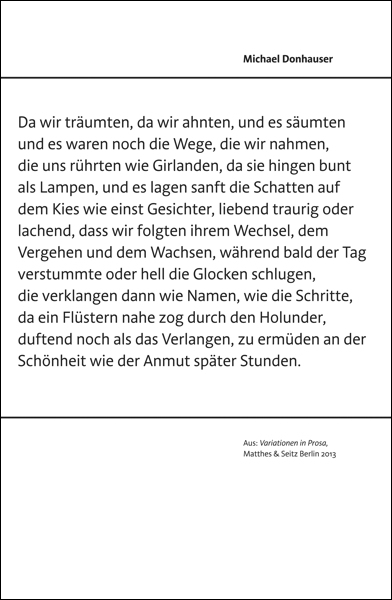
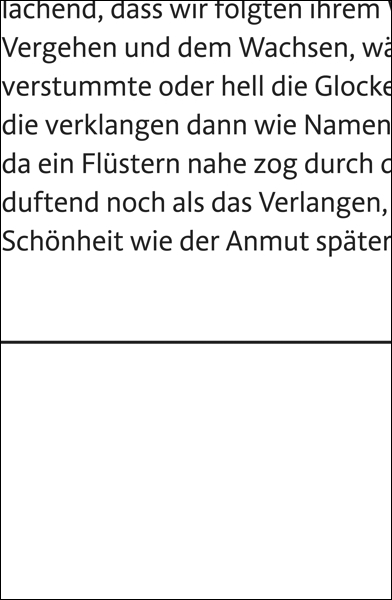
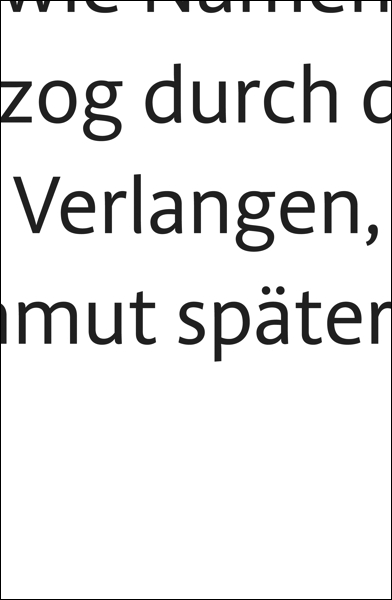
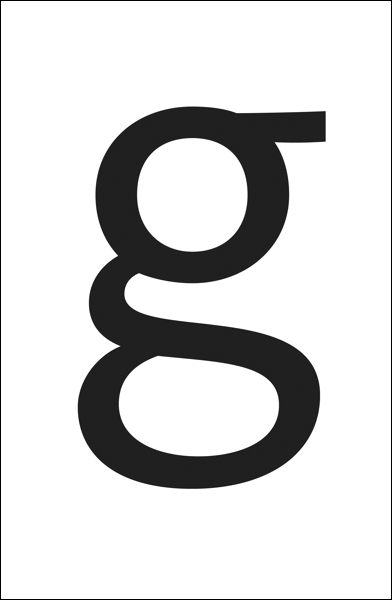
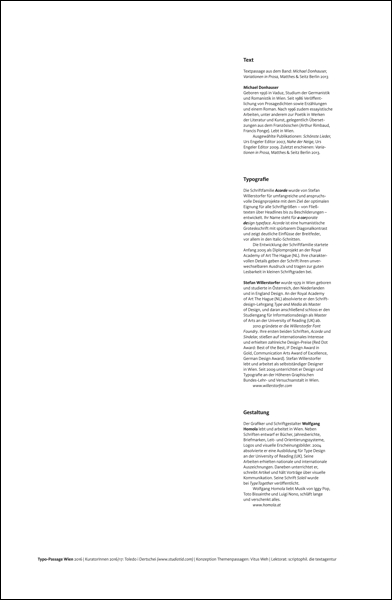
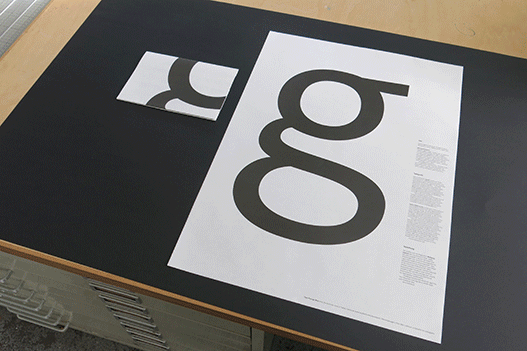
Text
Textpassage aus dem Band: Michael Donhauser, Variationen in Prosa, Matthes & Seitz Berlin 2013. Michael Donhauser, geboren 1956 in Vaduz, Studium der Germanistik und Romanistik in Wien. Seit 1986 Veröffentlichung von Prosagedichten sowie Erzählungen und einem Roman. Nach 1996 zudem essayistische Arbeiten, unter anderem zur Poetik in Werken der Literatur und Kunst, gelegentlich Übersetzungen aus dem Französischen (Arthur Rimbaud, Francis Ponge). Lebt in Wien. Ausgewählte Publikationen: Schönste Lieder, Urs Engeler Editor 2007, Nahe der Neige, Urs Engeler Editor 2009. Zuletzt erschienen: Variationen in Prosa, Matthes & Seitz Berlin 2013.
Typografie
Die Schriftfamilie Acorde wurde von Stefan Willerstorfer für umfangreiche und anspruchsvolle Designprojekte mit dem Ziel der optimalen Eignung für alle Schriftgrößen – von Fließtexten über Headlines bis zu Beschilderungen – entwickelt. Ihr Name steht für a corporate design typeface. Acorde ist eine humanistische Groteskschrift mit spürbarem Diagonalkontrast und zeigt deutliche Einflüsse der Breitfeder, vor allem in den Italic-Schnitten. Die Entwicklung der Schriftfamilie startete Anfang 2005 als Diplomprojekt an der Royal Academy of Art The Hague (NL). Ihre charaktervollen Details geben der Schrift ihren unver wechselbaren Ausdruck und tragen zur guten Lesbarkeit in kleinen Schriftgraden bei. Stefan Willerstorfer wurde 1979 in Wien geboren und studierte in Österreich, den Niederlanden und in England Design. An der Royal Academy of Art The Hague (NL) absolvierte er den Schriftdesign-Lehrgang Type and Media als Master of Design, und daran anschließend schloss er den Studiengang für Informationsdesign als Master of Arts an der University of Reading (UK) ab. 2010 gründete er die Willerstorfer Font Foundry. Ihre ersten beiden Schriften, Acorde und Sindelar, stießen auf internationales Interesse und erhielten zahlreiche DesignPreise (Red Dot Award: Best of the Best, iF Design Award in Gold, Communication Arts Award of Excellence, German Design Award). Stefan Willerstorfer lebt und arbeitet als selbstständiger Designer in Wien. Seit 2009 unterrichtet er Design und Typografie an der Höheren Graphischen BundesLehr und Versuchsanstalt in Wien. www.willerstorfer.com
Gestaltung
Der Grafiker und Schriftgestalter Wolfgang Homola lebt und arbeitet in Wien. Neben Schriften entwarf er Bücher, Jahresberichte, Briefmarken, Leit und Orientierungssysteme, Logos und visuelle Erscheinungsbilder. 2004 absolvierte er eine Ausbildung für Type Design an der University of Reading (UK). Seine Arbeiten erhielten nationale und internationale Auszeichnungen. Daneben unterrichtet er, schreibt Artikel und hält Vorträge über visuelle Kommunikation. Seine Schrift Soleil wurde bei TypeTogether veröffentlicht. Wolfgang Homola liebt Musik von Iggy Pop, Toto Bissainthe und Luigi Nono, schläft lange und verschenkt alles. www.homola.at